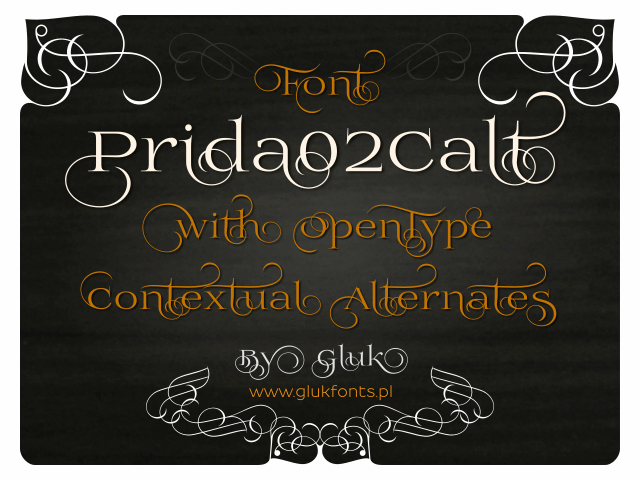
A fonte Prida02Calt é uma elegante escolha para designers que buscam adicionar um toque único a seus projetos impressos ou digitais. Embora seja classificada como Blackletter, sua tipografia característica traz à tona um aspecto arquitetônico e sombrio sem ser assustador. Ainda em constante evolução, essa fonte é especialmente adequada para trabalhos que precisam de uma cara específica e a Prida02Calt requer suporte do OpenType com alternâncias contextuais para atingir seu máximo potencial. O designer responsável pela criação dessa elegância é Hamilton. Suas escolhas criativas resultaram em um conjunto de fontes únicas que se destacam no universo dos recursos gráficos, oferecendo tanto opções simples quanto detalhadas dependendo do projeto específico. Seja para fins comerciais ou pessoais, a Prida02Calt é uma excelente adição à sua coleção de ferramentas digitais. Com seu suporte ao OpenType contextual alternativas, essa fonte se destaca por permitir que designers e desenvolvedores de web tenham mais controle sobre o resultado final. A Prida02Calt oferece não apenas um design atraente, mas também um poderoso auxílio para garantir uma experiência visual perfeita em vários ambientes digitais. Para quem aprecia tanto seu charme quanto sua capacidade de personalização e adaptação, o Prida02Calt é uma escolha inteligente. Esta fonte não apenas oferece um conjunto único de caracteres, mas também abraça as necessidades específicas do usuário ao permitir a manipulação contextual que faz toda a diferença em seus projetos.